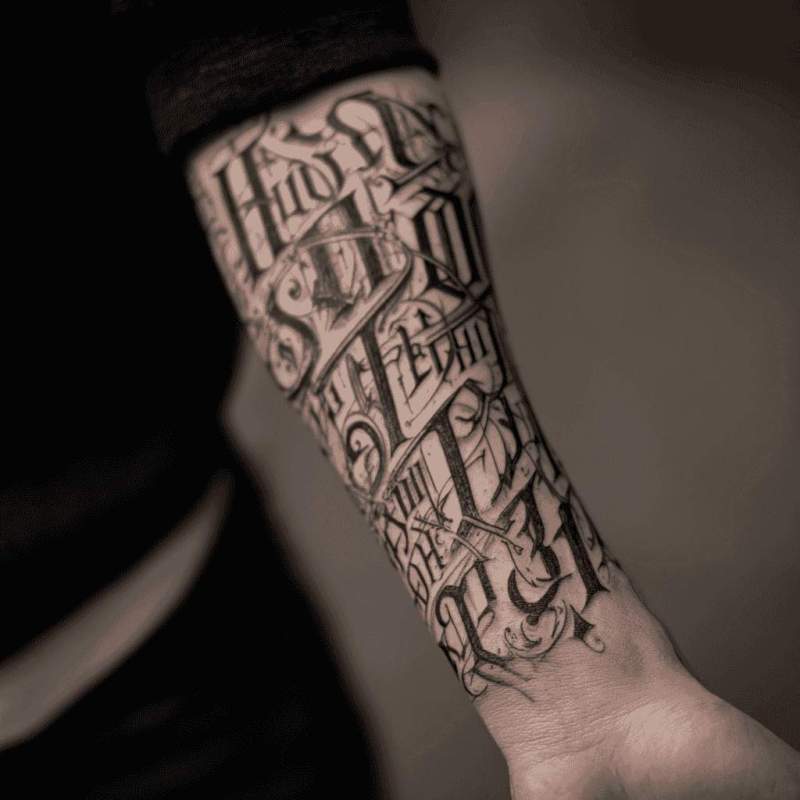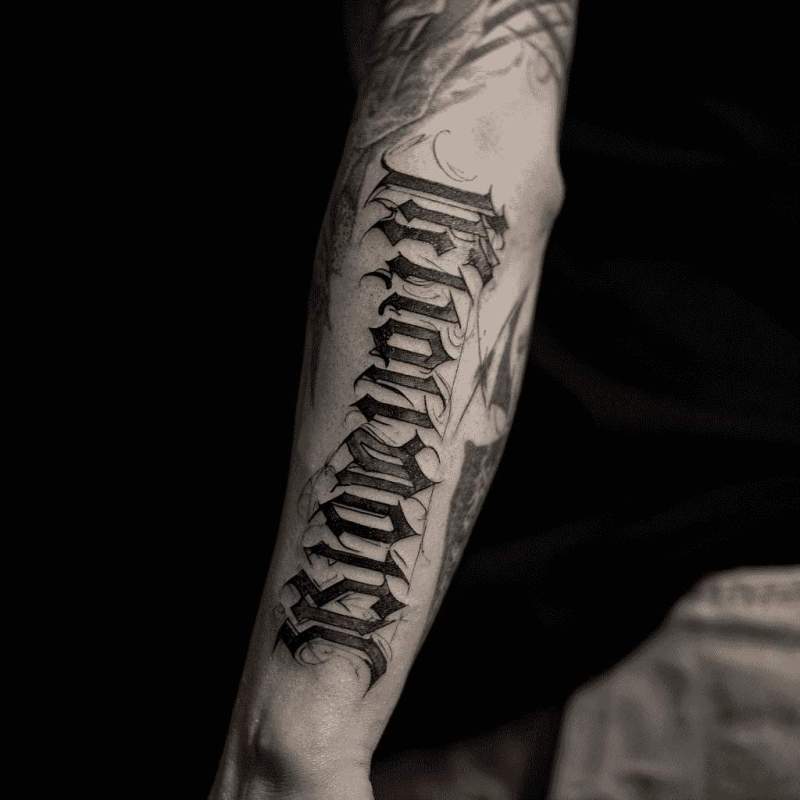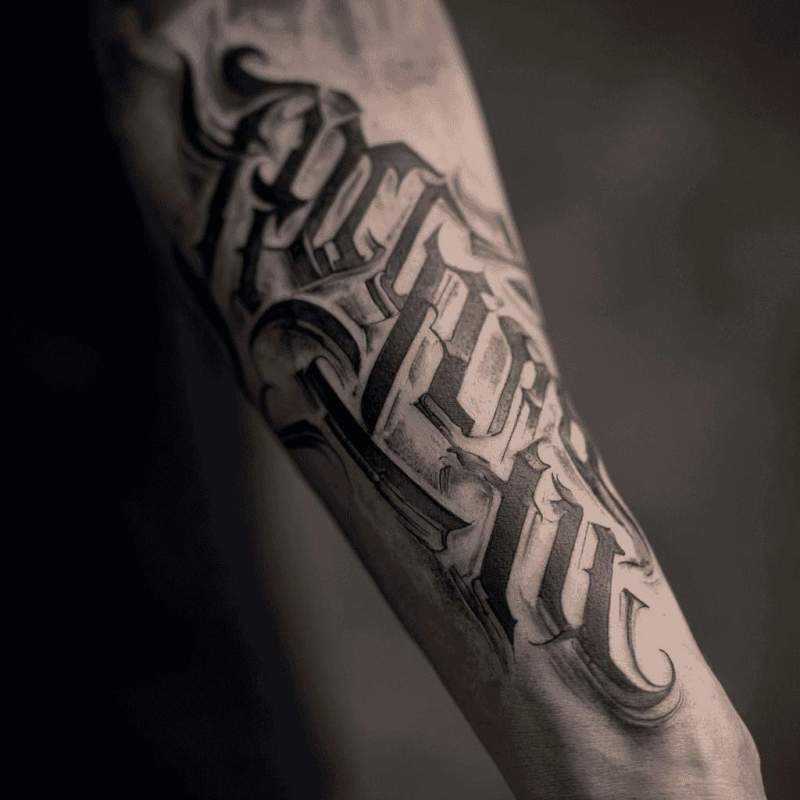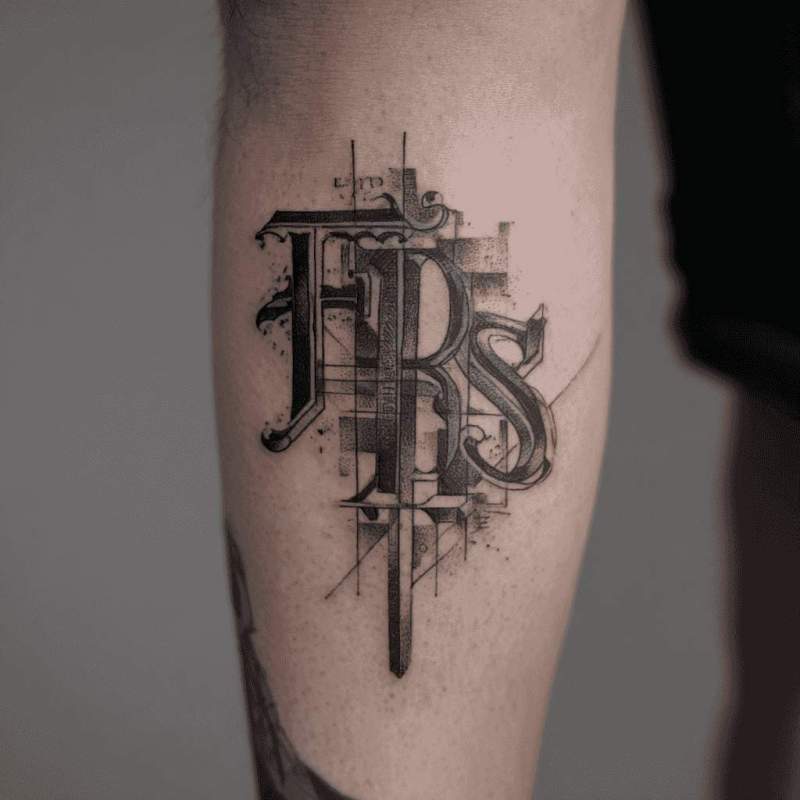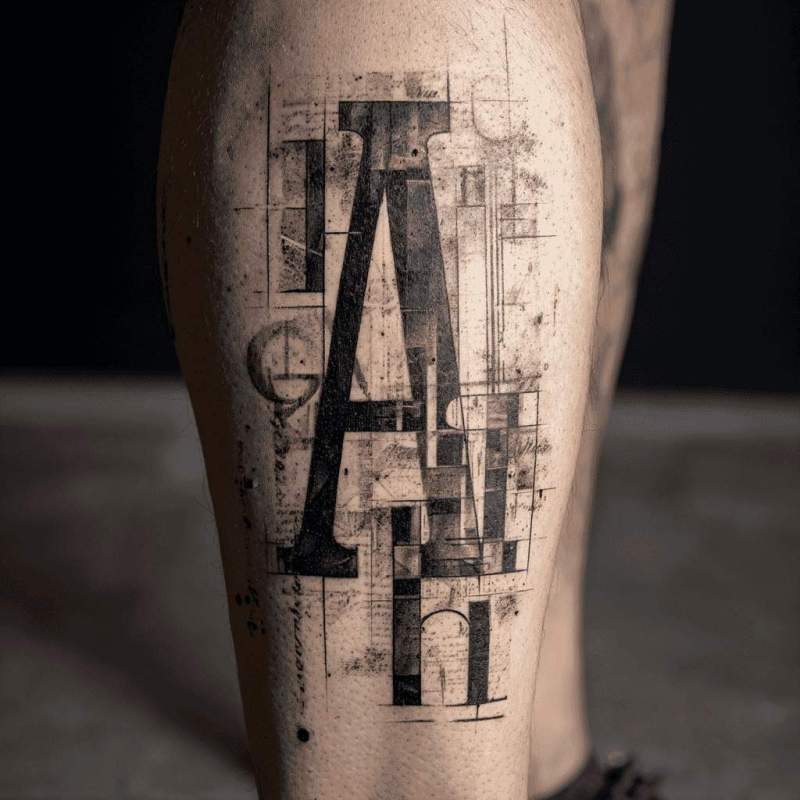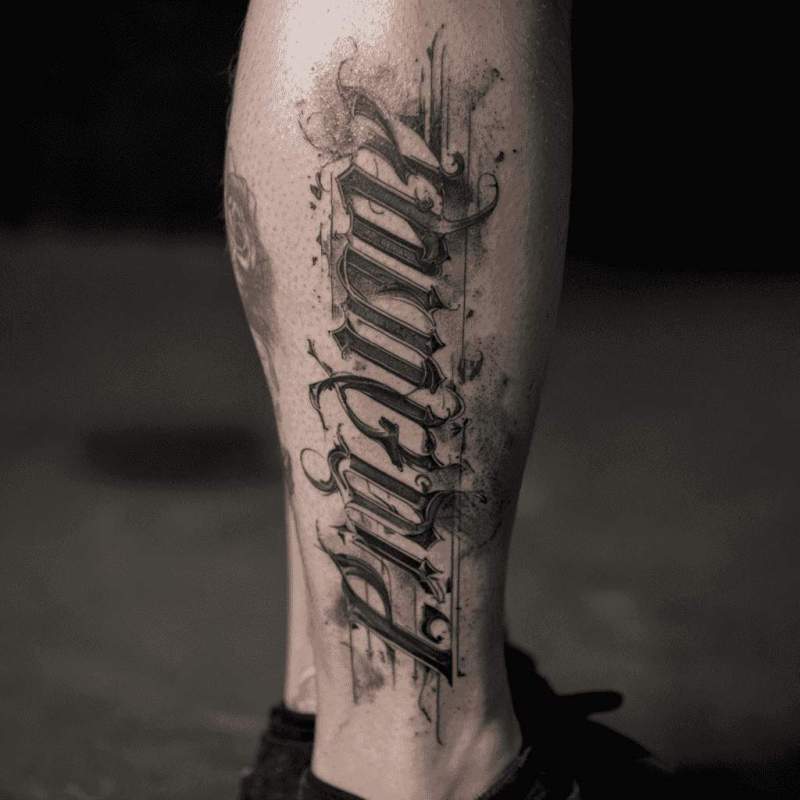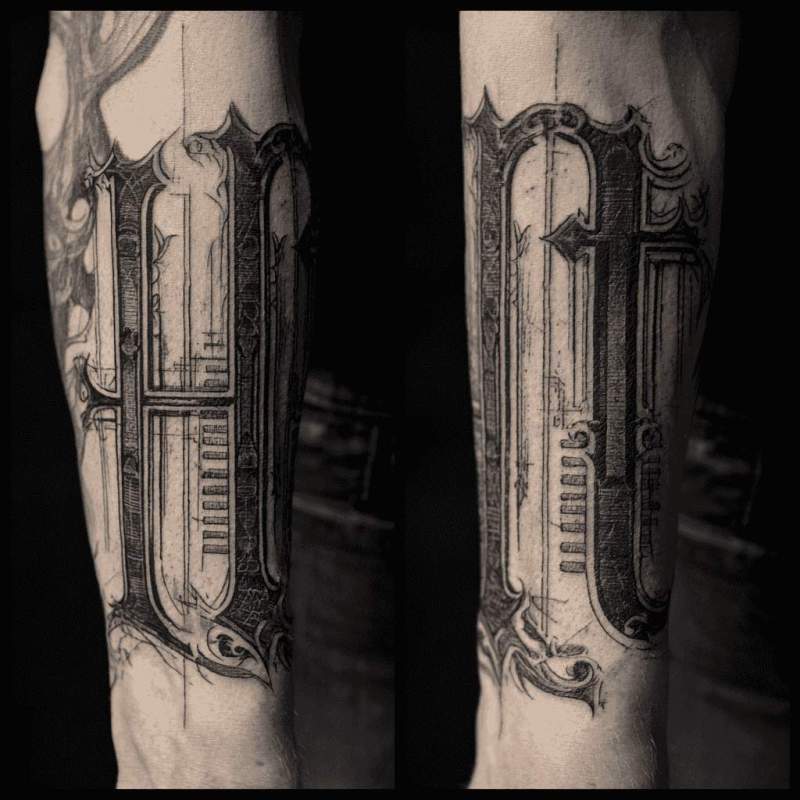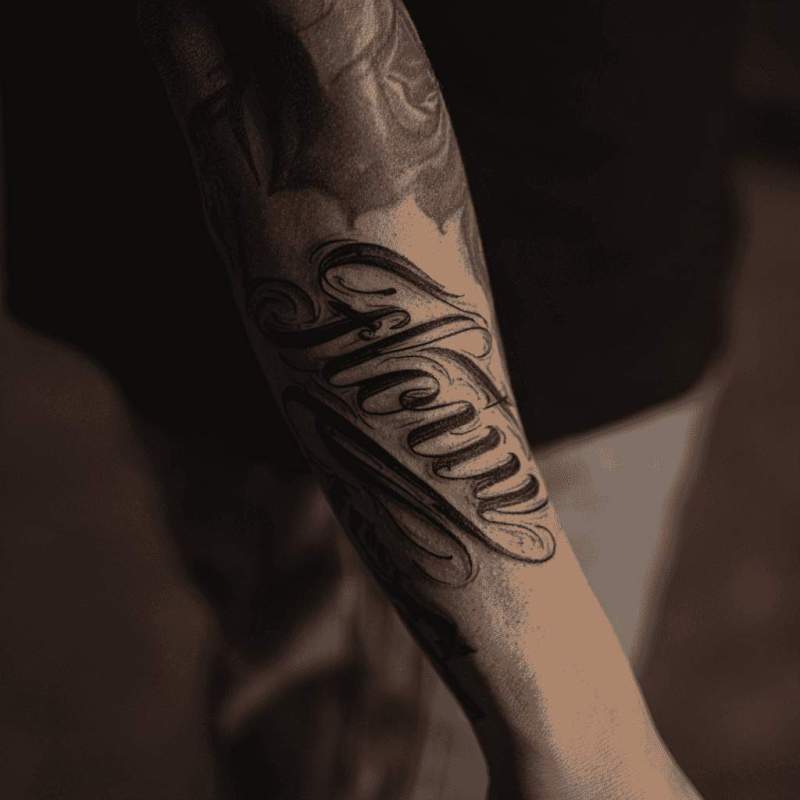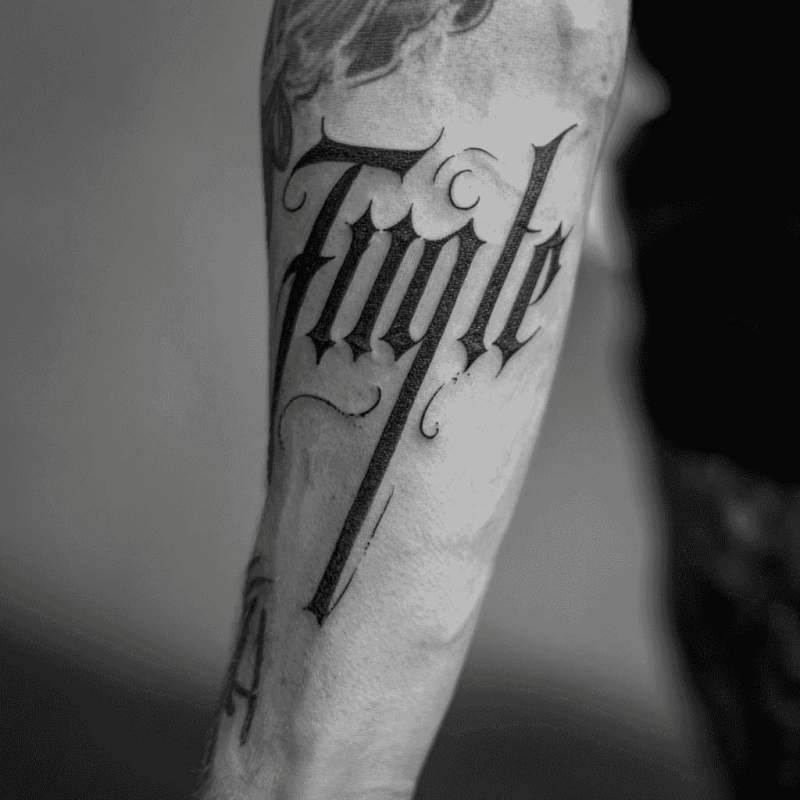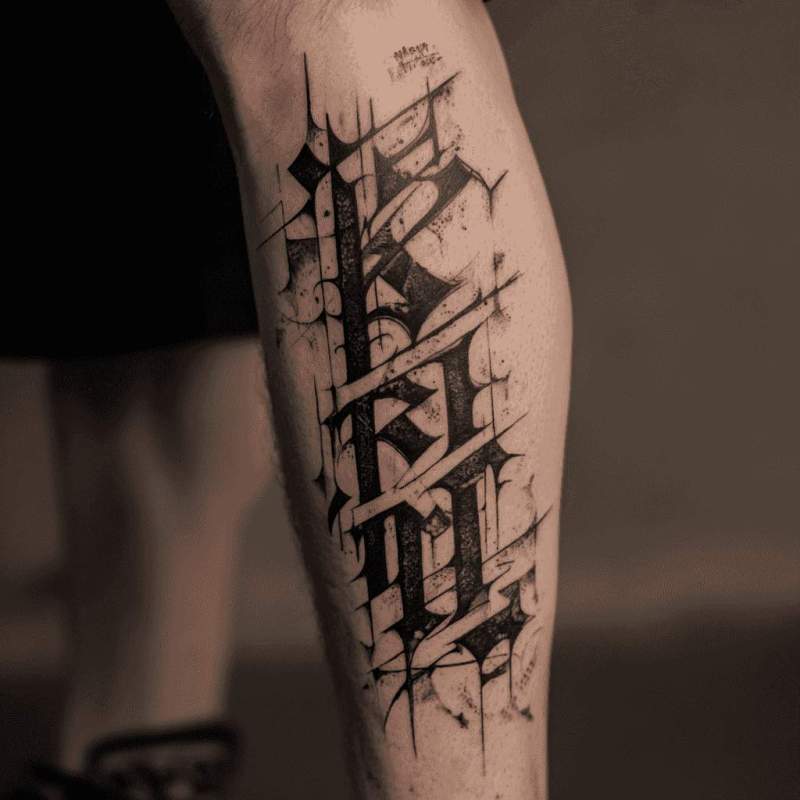
Die besten Schriftarten Tattoo Designs in Schweiz (2025)
Verlangst du nach eleganten Schriftarten für Tattoos? Die Typography-Tattoo-Meister von Lebende Legend Tattoo in Bern, Schweiz haben die besten Font-Styles kuratiert, um dir Lettering-Inspiration zu bieten.
Was symbolisiert ein Schriftarten tattoo?
Schriftarten-Tätowierungen verwandeln Texte in künstlerische Ausdrucksformen durch typografische Vielfalt. Diese Designs können klassische Kalligrafie, moderne Fonts oder handgeschriebene Stile umfassen. Die Schriftart-Auswahl beeinflusst die Wirkung und Bedeutung der Botschaft erheblich.